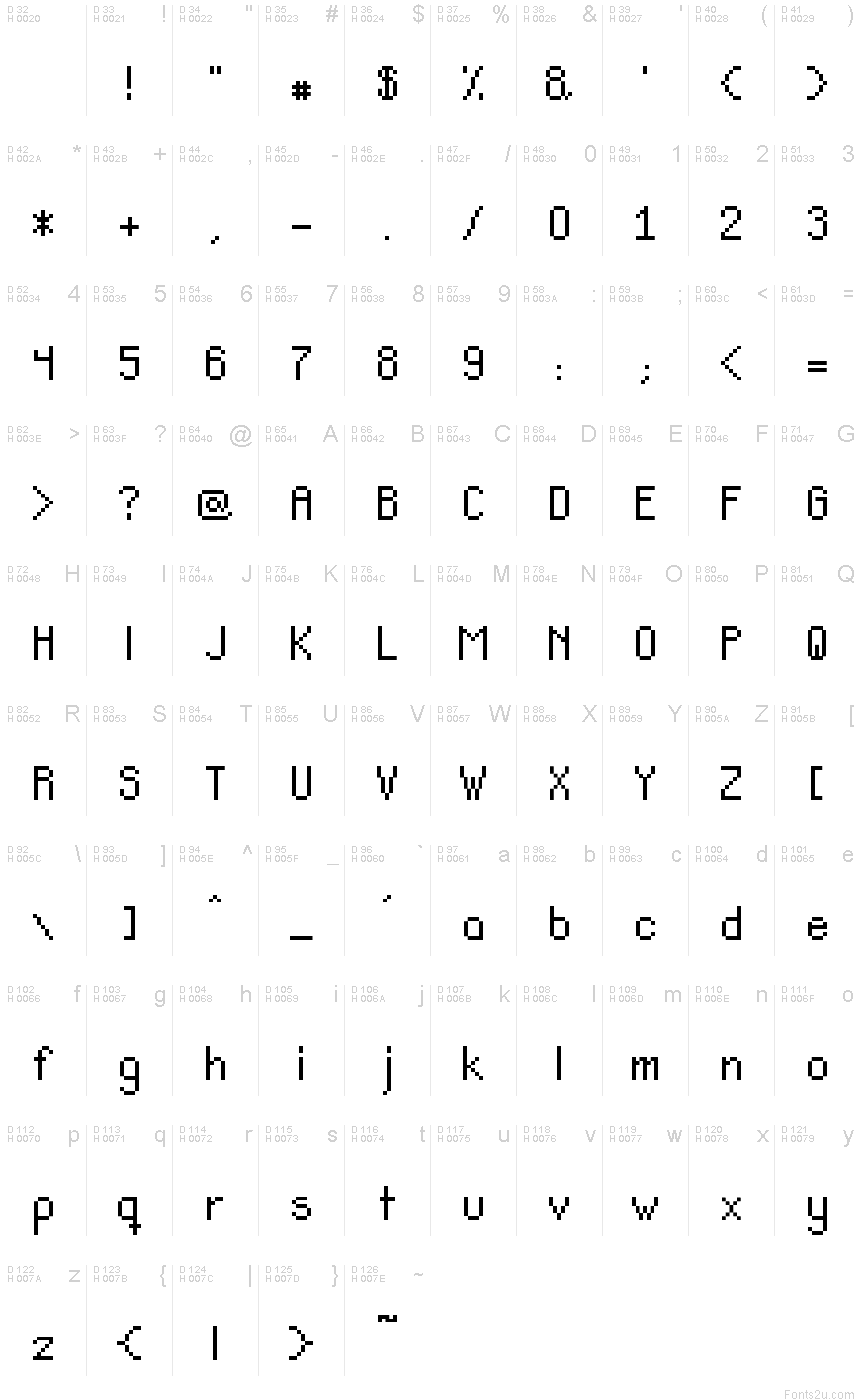
Podgląd czcionki Teachers Pet Sans Serif
Teachers Pet Sans Serif od Orgdot to darmowy font bitmapowy w stylu pixel art, utrzymany w przyjaznym klimacie szkolnych komputerów. Litery zbudowane są z wyrazistych, kwadratowych bloków i otwartych kształtów, co nadaje im prosty, swojski rytm – kojarzący się bardziej z programami edukacyjnymi i wczesną grafiką ekranową niż z wygładzonymi krojami bezszeryfowymi.
Świetnie sprawdzi się w grafice aplikacji retro, plakatach edukacyjnych, interfejsach gier, nagłówkach zinów czy tytułach na stronach internetowych, gdzie darmowy font pozwala wprowadzić nostalgiczny klimat wczesnej informatyki. Dzięki temu, że kształty są proste i ciepłe, a nie futurystyczne, font sprawdzi się również w krótkich etykietach i tekstach okładkowych, które potrzebują pixelowych krawędzi bez chłodnego, technicznego wyrazu.